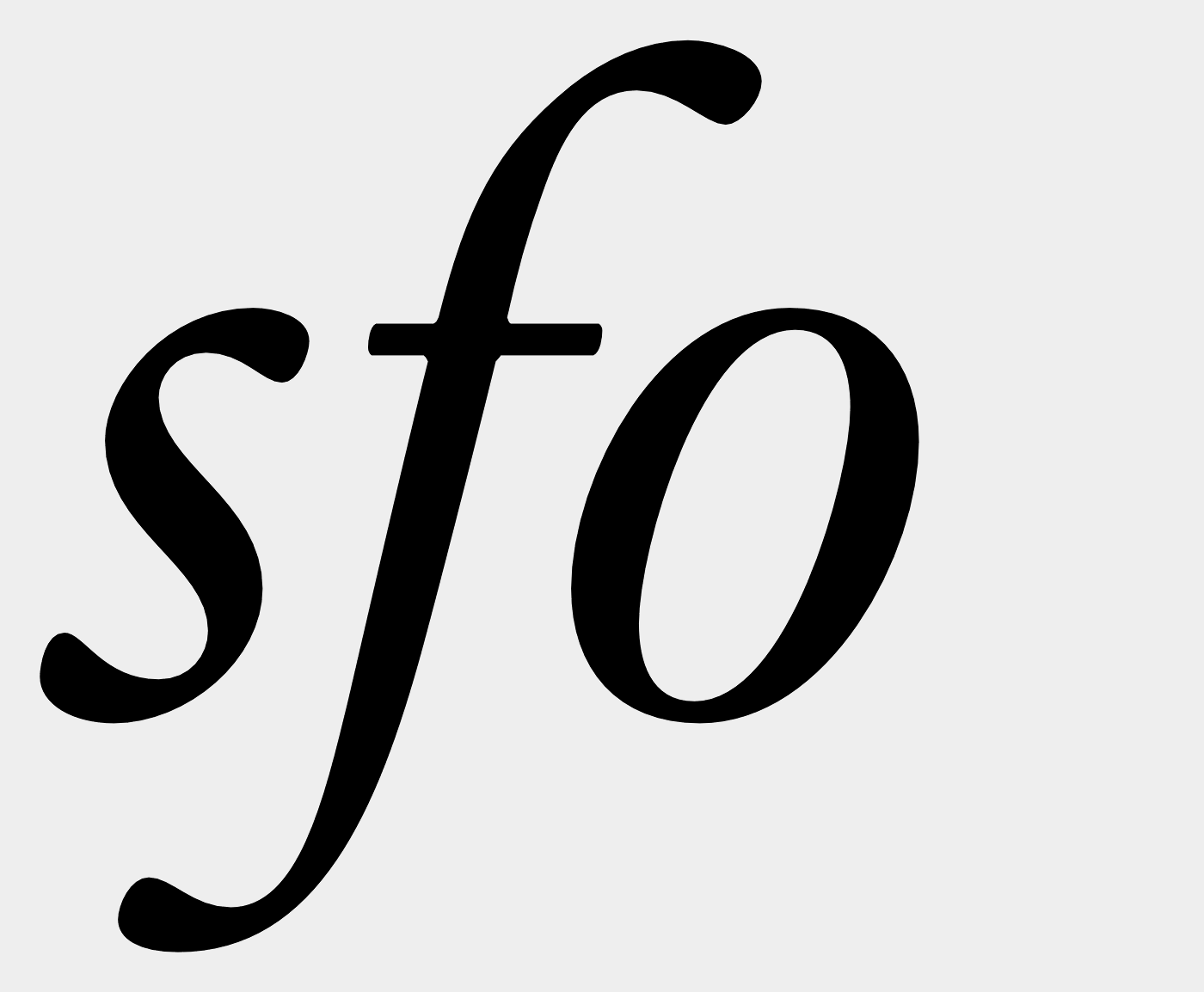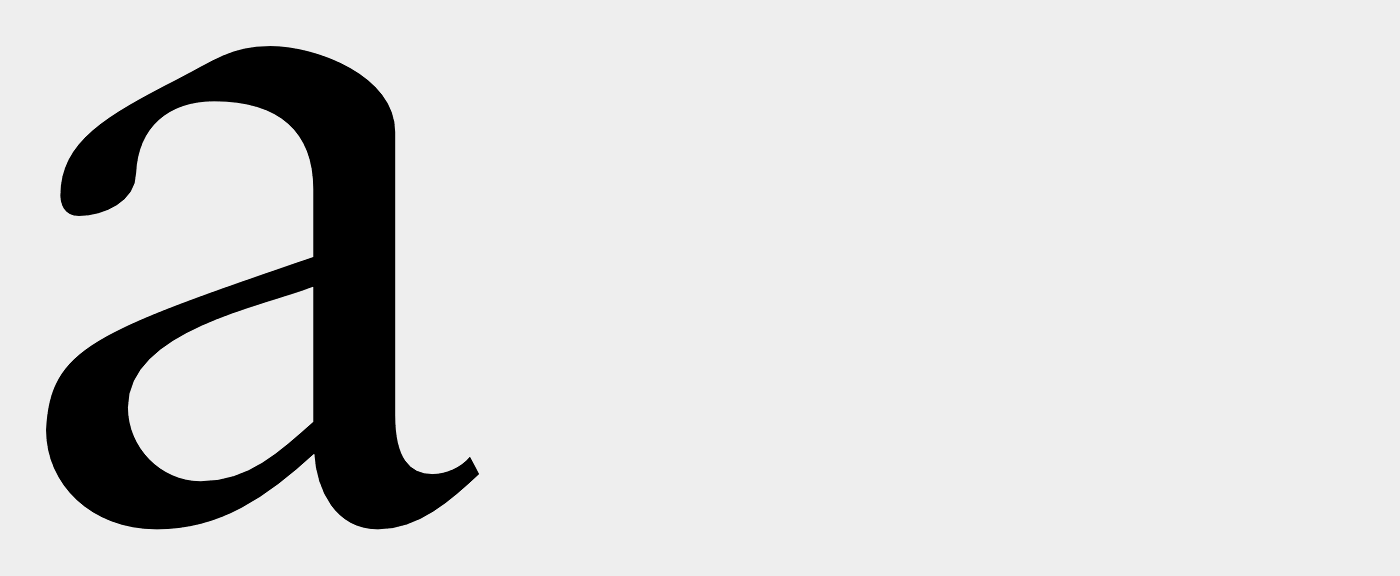
Detaillierter Font-Vergleich (LT, MT, Adobe etc.)
Ich bin neu hier bei Typografie.info. Aus irgendeinem Grund funktioniert bei mir Typophile nicht mehr (die Seiten bauen sich nicht auf), und auf der Suche nach einem Alternativforum bin ich (wahrscheinlich viel zu spät) hier angekommen. Ich bin eigentlich Biologie, aber nebenbei Hobbydesigner und Typografiefreund.
Ich plane eigentlich seit längerem, mir Sabon als Font zu kaufen. Eigentlich würde ich ja gerne Sabon Next haben, aber das ist preislich ja schon ein kleiner Happen. Außerdem gefällt mir das kleine a dort nicht so recht (sieht mir zu sehr nach einem Garamond-a aus). Deshalb wird es wahrscheinlich eine der alternativen Sabon-Fonts werden. Dazu meine Frage: Gibt es eine Möglichkeit, die einzelnen digitalen Schnitte mal im Detail zu vergleichen? Es gibt ja eine Version von Adobe, eine von Linotype, eine von Monotype - wonach entscheidet man da, was man will? Die Monotype wirkt sehr dünn. Adobes Version sieht sehr elegant aus, aber unterscheidet die sich (abgesehen vom Preis) eigentlich von der von Linotype?
Ich fürchte, ich könnte da etwas Beratung gebrauchen. Oder einen Schubs auf die richtige Webseite für sowas.
Außerdem gefällt mir das kleine a dort nicht so recht (sieht mir zu sehr nach einem Garamond-a aus).
Nicht nur das kleine a. Die Sabon ist ja als eine Variation der Garamond anzusehen.
Vielleicht habe ich mich auch etwas zu missverständlich ausgedrückt. Mir war schon klar, dass Sabon in gewisser Weise eine Garamondschrift ist. Aber das "a" von Sabon Next sieht doch arg nach Garamond aus, während sich das Sabon-"a" ziemlich auffällig davon abhebt. Na ja, mir ist zumindest Sabon erstmals durch das "a" aufgefallen und deshalb finde ich es schade, dass das bei Sabon Next so verloren ging.
Wegen dieser kleinen Unterschiede frage ich mich nur, ob es solche Variationen auch zwischen den einzelnen Sabon-Schnitten gibt. Es wäre echt schön, wenn man z.B. einzelne Glyphen von Monotype direkt im Vergleich zu der Adobe-Version sehen könnte. Das wäre auch generell nett, nicht nur für Sabon. So eine Kaufentscheidung ist bei den ganzen Varianten irgendwie nicht einfach für nen Laien ...
Es wäre echt schön, wenn man z.B. einzelne Glyphen von Monotype direkt im Vergleich zu der Adobe-Version sehen könnte.
Ansonsten behilft man sich gern mit den Übersichten von MyFonts, die man auch sehr groß ziehen kann:
Ralf, ich wusste gar nicht, dass MyFonts die so groß macht. Ich war überrascht wie viel Details man zu sehen kriegt (obwohl ich es nicht geschafft habe, das a so groß zu ziehen wie deines).
Beim direkten Vergleich einiger weniger Glyphen (ist ja schon etwas mühsam), fällt auf jeden Fall deutlich auf, dass Monotype Sabon schmaler und zierlicher ist. Na ja, schade, ich hatte gehofft, man kann die online irgendwie übereinander legen lassen oder so.
R::bert, ich hatte Sabon an der Uni für die Abschlussarbeit benutzt und mich da ein wenig rein verschossen. Jetzt wollte ich sie für den privaten Zweck auch mal haben. Nur so aus Interesse, welches ist denn deiner Meinung nach eine modernere Alternative? Ich lasse mich ja gerne überzeugen. ;-)
Hallo Nils,
ich habe mal einen schnellen Vergleich der Sabon MT Pro, Sabon LT Std und der Sabon Next LT Pro gebastelt. Ich hoffe, das hilft dir weiter.
Im Prinzip ist die Next schon deutlich besser, was die Kurven angeht und viele Details sind wesentlich charaktervoller Ausgearbeitet, was mich aber deutlich enttäuscht ist die Kursive. Da sind manche Zeichen einfach zu aufgeräumt: das breite o aus der LT-Std-Version wurde angepasst, das s war vorher wesentlich kalligrafischer, ich finde das neue zu glatt gehobelt und standardmäßig wird auf das doppelt geschwungene f zurückgegriffen, das unten gerade auslaufende gibt es zwar immer noch, muss aber über die Glyphentabelle eingefügt werden. Gerade die letztgenannten fand ich sehr sabontypisch ...
Aber sich sehe gerade, dass in der eText-Version auf die alten Entwürfe zurückgegriffen wurde  :biglove:
wenn es die sabon sein soll, dann würde ich – ganz subjektiv – die sabon next wählen. ich finde sie aus drei gründen der alten linotype sabon überlegen (die von monotype würde ich nicht mal in betracht ziehen, weil sie keine kursiven kapitälchen hat):
erstens fällt mir auf, dass die alte sabon bei der digitalisierung mager geraten ist. gerade wenn du dokumente zu hause ausdrucken willst, musst du davon ausgehen, dass die sabon next – wie das vergleichsdokument zeigt – mehr farbe aufs papier bringt. das halte ich für positiv.
Außerdem wird klar, warum es bei den Duplex-Matrizen keine überhängende Buchstabenteile geben konnte. Das verbietet das hoch- und runterschieben der Matrize. Deswegen wurden in der Sabon italic das f und das j linksunten gekürzt, und fehlt auch die linke Serie vom p. Also nicht weil Tschichold das so toll fand, es war einfach eine technische Begrenzung. Quasi als Trostpflaster gab es bei Stempel eine Handsatzversion der Sabon, der diese Eigenheiten nicht aufwies. Die größeren Graden mussten ja nicht kompatibel mit der Linotype sein, weil es diese auf der Linotype nicht gab. Es war also höchster Zeit, dass Linotype die Sabon Next hat machen lassen.